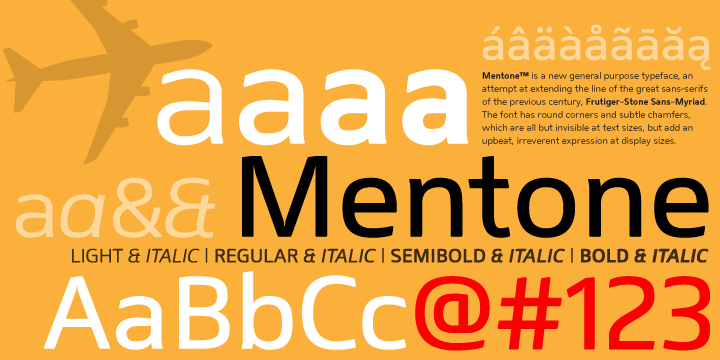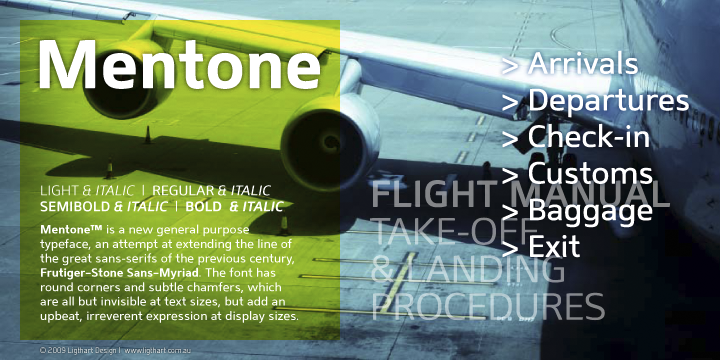
Mentone - Jan Schmoeger, Paragraph
Mentone is a new general purpose typeface, an attempt at extending the line of the great sans-serifs of the previous century, Frutiger - Stone Sans - Myriad.
The font has round corners and subtle chamfers, which are all but invisible at text sizes, but add an upbeat, irreverent expression at display sizes.
The typeface is named after the beautiful bayside suburb of Melbourne, Australia, where the designer lives.
Sowas versteh ich immer nicht. Gehen die Leute davon aus, dass ein und derselbe Schnitt sowohl für ernsthaften Textsatz als auch für Display funktionieren soll?
Warum denn nicht? Natürlich ist es so, dass es mittlerweile für alle möglichen Satzgrößen optimierte Schnitte gibt. Aber eben auch nur bei vielen Highend-Schriftfamilien – bei kleineren Schriftfamilien (von ebenso kleinen Foundrys) ist ein Displayschnitt meist schon Luxus. Und abgerundete Ecken sind ja nun wirklich Feinheiten, die entscheidend von der Einsatzgröße abhängig sind und auch sonst kaum einen allzu großen Einfluss auf die Form haben (im Gegensatz von Ink-Traps beispielsweise).
Hast du denn immer die Möglichkeit, entsprechend der Schriftgrößen auch die passenden Schnitte wählen zu können?
Gehen die Leute davon aus, dass ein und derselbe Schnitt sowohl für ernsthaften Textsatz als auch für Display funktionieren soll?
Warum denn nicht?
Weil ein Textschnitt ein anderes Tier ist als ein Displayschnitt. Zumindest solang wir nicht davon sprechen, dass etwas irgendwie mehr oder weniger in der Größe funktioniert, sondern sich wirklich gut *lesen* soll (im Sinn von readability, nicht legibility). Und ich meine jetzt nicht offensichtliche optische Korrekturen wie Inktraps oer so, sondern das Gesamtkonzept, die vertikalen Proportionen, die Divergenz der Einzelformen, nicht zuletzt die Zurichtung (usw., usw). Um Hrant Papazian zu zitieren (der zugegeben eine *sehr* ernsthafte / konsequente Einstellung zum Thema Textschriften hat): "In effect, a text font has to have a certain ugliness to do its job". Was sich mit Displaygrößen nun mal eher schlecht verträgt.
Hast du denn immer die Möglichkeit, entsprechend der Schriftgrößen auch die passenden Schnitte wählen zu können?
"Luxus" kann ich mir nicht leisten, aber ich versuche schon, den Schriften gerecht zu werden, die ich verwende.
War ja auch mehr eine Frage – wollte jetzt den Thread nicht entgleisen damit. Und gegen die Mentone hab ich sonst auch nix.
Gehen die Leute davon aus, dass ein und derselbe Schnitt sowohl für ernsthaften Textsatz als auch für Display funktionieren soll?
Warum denn nicht?
Weil ein Textschnitt ein anderes Tier ist als ein Displayschnitt. Zumindest solang wir nicht davon sprechen, dass etwas irgendwie mehr oder weniger in der Größe funktioniert, sondern sich wirklich gut *lesen* soll (im Sinn von readability, nicht legibility). Und ich meine jetzt nicht offensichtliche optische Korrekturen wie Inktraps oer so, sondern das Gesamtkonzept, die vertikalen Proportionen, die Divergenz der Einzelformen, nicht zuletzt die Zurichtung (usw., usw). Um Hrant Papazian zu zitieren (der zugegeben eine *sehr* ernsthafte / konsequente Einstellung zum Thema Textschriften hat): "In effect, a text font has to have a certain ugliness to do its job". Was sich mit Displaygrößen nun mal eher schlecht verträgt.
Ja, das ist mir alles klar und ich bin da vollkommen deiner Meinung, dass wenn sich die Möglichkeit ergibt, man die Schrift(-schnitte) auch in den Bereichen einsetzen sollte, für die sie optimiert wurde.
Ich fand nur deine Formulierung etwas hart, die auf mich so wirkte, als dass es ausgeschlossen ist, dass ein Textfont auch mal in Displaygröße gesetzt werden kann und man dennoch eine »ernsthafte« Gestaltung abliefert.
Ist für mich grundsätzlich schon so. Zumindest theoretisch (was also nicht heißt, dass ich es nicht auch schon mal gemacht hätte [ist ja alles ein Lernprozess :-) ]).
Wenn man das tut, muss man halt wissen, dass man gewisse «hässliche» Details (wenn wir wirklich von Textfonts reden) «ans Licht kehrt». Aber ich bin da vielleicht unüblich puristisch eingestellt, ich krieg zB auch Alpträume von groß sichtbaren Inktraps.
Mir gefällt sie gar nicht, ich finde z.B. das M unausgewogen breit mit einer völlig übertriebenen Tintenfalle. :oops:
da sieht man wieder, wie aktuell howard gossage noch immer ist:
In was für einer Welt lebt der Grafiker oder Art-Direktor? Was sieht er wirklich, wenn er etwas anblickt?
Ein Beispiel. Ich kaufte unlängst eine elektrische Schreibmaschine mit einer der heute so beliebten modernen Schrifttypen. Marget Larsen, eine der größten Kapazitäten unter allen Grafikern und Art-Direktoren der Welt, kam in mein Büro und bewunderte die Maschine. Ich tippte ein paar Worte herunter und fragte, was sie von der Schrift hielte.
Sie sah sie gedankenvoll an und sagte: »Sehr nett, nur sollten Sie das große M nie verwenden.«
Warum sollen australischen Designer nicht auch völlig uberflüssige Schriften gestalten dürfen. Das ist der Trend. Die Diskussion Textschrift-Displayschrift halte ich hier für deplatziert und in sich nicht für ergiebig. Nachwievor gehe davon aus das sich hier Experten gegenseitig motivieren und über maches muß doch bitte nicht immer wieder alles von vorne diskutiert werden.